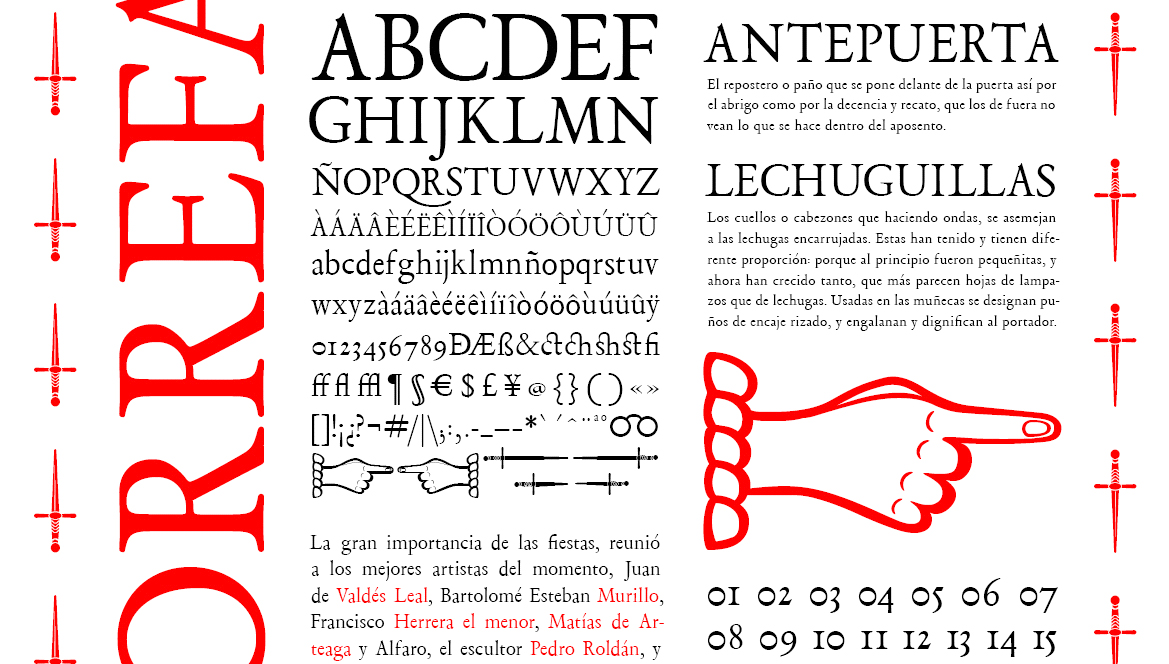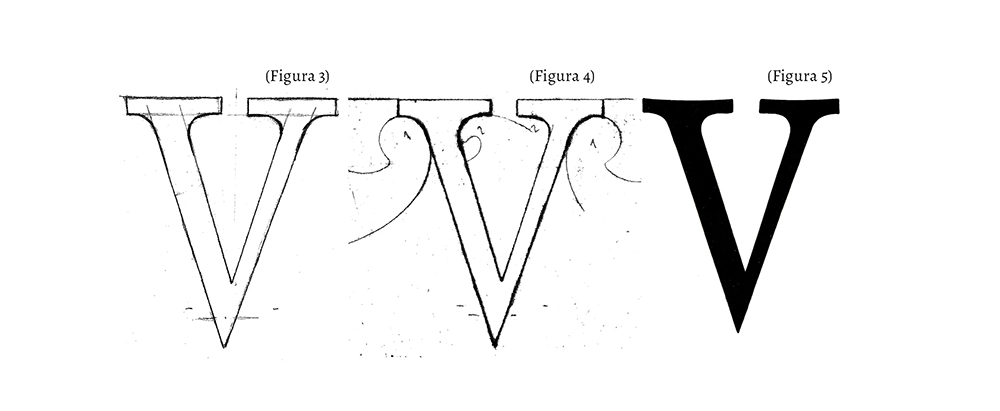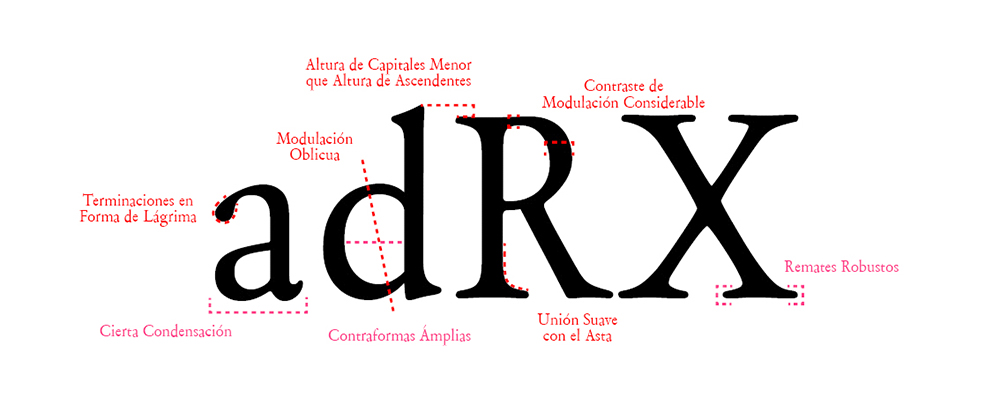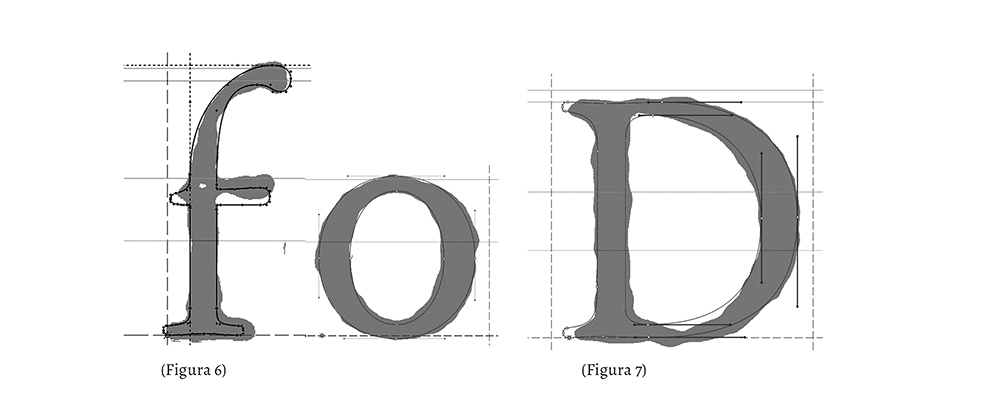
TorreFarfan es una remasterización digital tipográfica, que tiene su origen en la tipografía barroca del siglo XVII empleada en la impresión del libro realizado con motivo de la canonización de San Fernando, escrito por Fernando de la Torre Farfán del que procede el nombre de la fuente, e impreso en Sevilla en 1671 por la Viuda de Nicolás Rodríguez de Ábrego. La obra recoge la descripción de las fiestas que celebró la Santa Iglesia Catedral de Sevilla y está considerada una obra maestra de la tipografía hispalense y la mejor edición de libro impreso de la España del seiscientos.
La recuperación de esta fuente tipográfica es el resultado de una investigación histórica realizada para la elaboración del proyecto fin de Estudios Superiores de Diseño Gráfico de la Escuela de Arte de Sevilla realizado por Estefanía González Sánchez, diseñadora gráfica, y bajo la tutela de Javier Navarro Moragas, doctor en Bellas Artes por la Universidad de Sevilla y profesor en semiótica tipográfica en la Escuela de Arte de Sevilla. La realización de este proyecto pretende poner en conocimiento de aquellos a los que le pueda interesar la arquitectura tipográfica en el periodo dorado de la imprenta en Sevilla para así dar a conocer la manera de hacer en esta época y en esta región. Ello ha permitido traer al presente parte de un patrimonio andaluz no tan conocido, concretamente desde el prisma de la edición del libro impreso, que nos permite entender una parte importante de esta cultura.
Remasterizar la póliza tipográfica de tan importante edición bibliográfica dentro del marco cultural de la ciudad hispalense en el siglo XVII nos permite recuperar matices estéticos del pasado. Por otro lado nos ofrece conocimiento sobre la manera de trabajar el libro impreso y más concretamente la tipografía de la época de que se trata. Es una puerta abierta a la investigación histórica del gremio de impresores sevillanos del XVII que a la vez permite y pretende la búsqueda de una gráfica unificadora entre pasado y presente.
Este artículo ofrece un análisis del contexto histórico, un estudio morfológico de la fuente que incluye comparativas arquitectónicas, así como la descripción del procedimiento realizado con el fin de materializar la recuperación de esta póliza tipográfica.
Contexto Histórico
Durante un periodo de cinco días en el mes de mayo del año 1671, siendo papa Clemente X, y reinando en España Carlos II El Hechizado, Sevilla realizó un festival religioso en el que la ciudad fue decorada con elementos ornamentales y arquitectura efímera para celebrar la canonización del rey San Fernando el III de Castilla y León (1201-1252), proclamado héroe cristiano por la conquista de grandes extensiones territoriales de Al-Andalus en el año 1248 pertenecientes a la cultura almohade. El cabildo de la catedral hispalense encargó al sacerdote, cronista, poeta, escritor y traductor Fernando de la Torre Farfán la autoría del libro Fiestas de la Santa Iglesia Metropolitana, y Patriarcal de Sevilla, al Nuevo Culto del Señor Rey San Fernando, con el fin de describir dichas fiestas con todo lujo de detalle y dejar constancia escrita de estos hechos. La realización del libro pretendía ser una reafirmación de la Sevilla barroca y un intento de recuperar la grandeza perdida tras la peste que afectó a casi la mitad de la población, por lo que la Catedral financió y distribuyó dos mil copias a Universidades, Catedrales y a personalidades ilustres de todo el mundo.
La gran importancia de las fiestas reunió a los mejores artistas de la Sevilla de la época, Juan de Valdés Leal (1622-1690), Bartolomé Esteban Murillo (1617-1682), Francisco Herrera el Menor (1627-1685) Matías de Arteaga y Alfaro (1633-1703), el escultor Pedro Roldán (1624-1699), y al retablista Bernardo Simón de Pineda (1638 – 1702). Junto a esta nómina excepcional de artistas y como reza al pié del frontispicio del libro, encontramos que fue impreso en Sevilla en casa de la Viuda de Nicolás Rodríguez de Ábrego en la calle Génova. Una imprenta que debió despuntar con respecto a las otras treinta y dos que trabajaban por aquel entonces en la ciudad, equiparándose en calidad artística y maestría a la de aquellos artistas que colaboraron en la efeméride conmemorativa.
De Nicolás Rodríguez de Ábrego se conoce una parte interesante de su historia; imprime desde 1637 a 1671, momento en el que toma el relevo de la imprenta su viuda. El siglo xvii fue un tiempo de crisis en lo que al libro impreso se refiere –a diferencia de lo que sucedía en la primera mitad del siglo xvi– cuando Sevilla era el principal centro productor de libros de Castilla; en el xvii las ediciones impresas fueron muy pobres abundando las obras pequeñas impresas con tipos desgastados y papel de mala calidad. En este periodo surge un formato editorial denominado «Relaciones de Sucesos», antecedente a la prensa escrita que hoy conocemos. Fue parte de la producción de la imprenta de Nicolás; era de factura mediocre pero muy rentable ya que se trataba de tiradas cortas, fáciles de hacer y de bajo coste, gozando por ello de gran salida en el mercado diario.
Existen por otro lado documentos que recogen información relacionada con unos pleitos que Nicolás tuvo con la inquisición por sus trabajos como impresor; a finales de marzo de 1641 el oidor de la Audiencia sevillana Juan de Góngora, inspeccionó la imprenta de Nicolás Rodríguez y encontró miles de libros impresos sin haber «sacado liçencia […] ni mostrado privilegio para ello»,(2) por lo que fue condenado a prisión bajo fianza y se le confiscaron las obras y le fueron requisados los útiles de impresión, aunque Nicolás pudo pagar la fianza y no entró en la cárcel. Quizá todo ello podría haber llevado a Nicolás a realizar este tipo de tiradas de poca extensión, probablemente para incrementar sus beneficios y remontar su economía de una manera relativamente cómoda y ágil; además la ubicación estratégica de su imprenta le permitiría realizar un gran número de ventas debido al elevado flujo de transeúntes del que gozaba la calle Génova (hoy Avenida de la Constitución) por su gran actividad mercantil procedente de las Indias.
Durante este periodo muchas mujeres se hicieron cargo de las imprentas de sus maridos cuando estos fallecieron, pero pocas de ellas firmaban con sus propios nombres. Cierto es que lo peor que le podía acaecer a una mujer era enviudar ya que ella y su familia entraban en estado de desprotección económica y social. Estas circunstancias llevaban a muchas a casarse con otros hombres relacionados normalmente con el gremio con el fin de que estos pasaran a regentar sus imprentas. En determinadas situaciones las viudas podían entrar en el mercado laboral, otorgándoles la posibilidad de realizar una actividad empresarial que por ellas mismas jamás habrían podido realizar. En los gremios se les permitía continuar la producción de sus difuntos maridos siempre y cuando pagaran los cánones marcados, y
este es el caso de la Viuda de Nicolás Rodríguez de Ábrego. De ella se tienen pocos datos; existe constancia que imprimió de 1671 (año en el que podría haber fallecido Nicolás) a 1674, o al menos es el periodo en el que los libros que salían de sus prensas lo hacían bajo su nombre. Todos los impresos realizados por ella son religiosos, de mayor complejidad y de una calidad superior a la habitual en la imprenta de Nicolás, además su obra engloba varios libros de una gran exquisitez. Otra de sus joyas editoriales la encontramos en el libro de Regla y Constituciones de la hermandad de Nuestra Señora del Socorro de Sevilla, que data de 1673. En este libro para la ya desaparecida Hermandad del Socorro, la Viuda de Nicolás colaboró de nuevo con Fernando de la Torre Farfán quién realizó la labor literaria, y con Matías de Arteaga y Alfaro responsable de los grabados ilustrativos. La Viuda, cuyo nombre desconocemos hasta la fecha, se codeó con los mejores artistas de la época, aumentó la producción al heredar la imprenta de su marido, y del mismo modo modificó el enfoque editorial del negocio.
Otro hecho que demuestra su gran valía empresarial es que su labor no solo se centró en la realización de libros impresos, sino que la armonizó con la tarea de mecenazgo, siendo impresos a su costa por otros impresores, como Tomé de Dios Miranda, libros de gran valor cultural como, Síguense siete romances a lo divino..; siendo la autoría del séptimo de estos romances atribuida a Lope de Vega.
No cabe dudar de la maestría proveniente de los talleres de esta mujer impresora que tiene el honor de ser la editora de la obra más encumbrada del arte impresor español del seiscientos. Según la historiadora Amalia Sarriá Rueda, el libro de la Fiestas de Torre Farfán «Es una obra maestra de la tipografía hispalense a cuya perfección contribuyen la selección del papel, la cuidada tipografía y las soberbias ilustraciones grabadas».(2)
Estudios Morfológicos
Paralelamente a la investigación histórica, se realizó un estudio de la arquitectura de los glifos que componen la póliza tipográfica del libro Torre Farfán. En este estudio observamos características pertenecientes a una época de transición tipográfica, ya que observamos una morfología de romana clásica, pero con rasgos evolutivos que la acercan hacia lo que mucho más tarde serán las romanas modernas. Por un lado, observamos algunas características comunes con las tipografías Garaldas, propias del siglo anterior, y que tienen como punto de partida las tipografías creadas por Francesco Griffo para Aldo Manucio en 1495.
En el siglo XVI Antonie Augereau y Claude Garamond realizarán tipografías con características ya asentadas de las tipografías Garaldas. Algunos rasgos de las tipografías Garaldas son: modulación oblicua, contraste de modulación considerable, remates inferiores unidos de manera suave con el asta, terminales de la /a/c/f/r/ con acabado en forma de lágrima, altura de las capitales menor que la de los astiles ascendentes..
La póliza utilizada por la Viuda de Nicolás Rodríguez tiene las características mencionadas, y por ello se engloba dentro de las tipografías Garaldas, pero también presenta rasgos modernizados que la situan en el marco espacio-temporal de las tipografías Barrocas o de transición, tan características desde mediados del siglo XVII hasta el siglo XVIII. Las tipografías de transición son un paso intermedio entre las romanas clásicas y las romanas modernas y tienen su punto de partida en la arquitectura de la Romain du Roi. Tienen muchas similitudes con las características de los tipos de Grandjean del siglo XVII. Algunos de estos rasgos podemos observarlos en nuestra tipografía, pero lo que sí es cierto es que en nuestro caso nos encontramos en un periodo temporal anterior a la creación de la Romain du Roi, por lo que se observa claramente que son tendencias que ya se venían dando en periodos anteriores y que estas características morfológicas serán recogidas y homologadas posteriormente por Grandjean en su Romain. Algunas características de las tipografías barrocas son: cierta condensación, contraformas amplias, remates robustos; estas características también podemos encontrarlas en nuestra tipografía.
Las tipografías de transición o barrocas se desarrollaron principalmente en Holanda, Inglaterra y Francia, pero el país con mayor peso en el ámbito de la tipografía fue Holanda, y en general los Países Bajos. Estas morfologías coinciden con los rasgos arquitectónicos própios de la época en la que se imprimió el libro, por lo que podemos decir que la tipografía usada para crear el libro de las fiestas de San Fernando era una tipografía vanguardista en su época, y no recuperada de tiempo atrás como era costumbre en este periodo.
En nuestra búsqueda por encontrar la identidad de la tipografía que nos ocupa nos encontramos con las pólizas empleadas en la prensa de la Universidad de Oxford, unas pólizas que tienen un adn similar a la empleada por la Viuda. Justo en ese mismo espacio temporal, concretamente un año más tarde de la impresión del libro de las fiestas de San Fernando, en el Reino Unido, John Fell –obispo y Vice-Canciller de la Universidad de Oxford–, creará la prensa de dicha universidad, y las tipografías empleadas pasarán a conocerse en aquella zona como «Tipos Fell». Dotó a su imprenta de las mejores tipografías existentes en el momento y para ello mandó comprar las pólizas más modernas y mejor realizadas de toda Europa. Para Fell el mejor lugar en el que podía abastecerse de las pólizas de mejor calidad era Holanda, ya que consideraba que la escuela tipográfica más exquisita residía en la estela de los punzonistas Garamond, Granjon y Van Dijk. Posteriormente, en la imprenta de Fell, estas pólizas fueron utilizadas para realizar impresiones de relevancia, como las ediciones de lujo, característica que también compartirá con la mujer impresora del libro de Torre Farfán. De las pólizas que adquirió Fell, destacamos unas romanas y unas itálicas inglesas, que son similares a las utilizadas por la Viuda. Las romanas y las versales fueron cortadas por Cristoffel Van Dijck y las itálicas por Robert Granjon y fueron adquiridas por Fell en 1672.
Entendemos que en la imprenta de la Viuda de Nicolás se conocían las tendencias tipográficas que se estaban dando en el momento, también sabemos que el Cabildo de la ciudad de Sevilla repartió dos mil copias del libro a los dignatarios más importantes de todo el mundo ¿Podría la Viuda de Nicolás, haberse convertido en modelo editorial, y de ese modo influir en la imprenta de la Universidad de Oxford, con la que compartía tantas características?
Cierto es que por el momento no hemos encontrado la identidad de la Viuda y no conocemos su historia, pero podemos estar seguros que se dedicaba a este oficio mucho antes de la realización del libro de Torre Farfán y que en su taller existía un gran nivel impresor, comparable con el proveniente de las principales capitales europeas en cuanto a arte tipográfico se refiere, y por supuesto quedó de manifiesto en esta obra.
Remasterización digital
En primer lugar, y con el fin de definir una tabla de caracteres adecuada, es preciso determinar las cualidades que va a cumplir nuestra tipografía, que vendrán sujetas por el uso que queremos que esta tenga. En nuestro caso, la fuente se realizó para texto corrido en prosa literaria, en castellano, y para uso actual. Esto nos llevó a realizar glifos como la /w/ o la /k/, partiendo de la morfología de otros de nuestro alfabeto que compartían similitudes arquitectónicas, ya que estas letras no se emplearon en el libro impreso. Además para ralizarlos acudimos a fuentes de estética paralela como la «Tipos Fell»descrita anteriormente con el fin de salvaguardar la analogía. Para nuestra tipografía se realizaron los glifos en minúscula y mayúscula, y vocales acentuadas; también se realizaron numerales elzevirianos, signos de puntuación, ligaduras y símbolos relacionados con el momento histórico al que pertenece.
Una vez definida la tabla de caracteres pasamos a la fase de digitalización de nuestra póliza realizando un estudio visual previo de cada uno de los glifos, agrupandolos por analogías formales según la metodología de Karen Cheng en su libro Diseñar tipografía. Esto nos facilitó la tarea posterior de digitalización del resto de la póliza. Los glifos por los que empezamos son /v/o/n/ de los que saldrán las siguientes relaciones:
- Del glifo /n/ derivan: /u/ñ/m/h/i/j/l/r/
- Del glifo /o/ derivan: /c/e/d/b/q/p/
- Del glifo /v/ derivan: /w/x/y/z/k/
- Los glifos /f/t/ guardan cierta similitud
- Los glifos /a/s/ pueden relacionarse con el /o/
Para las mayúsculas, el primer glifo que realizamos fue /H/, ya que su espesor se relaciona con /n/ que determinará el espesor del resto de mayúsculas:
- Del glifo /H/ derivan: /E/F/I/L/T/
- Del glifo /O/ derivan: /C/Q/G/D/
- Del glifo /B/ derivan: /P/R/
- Del glifo /U/ derivan: /J/
- Del glifo /N/ derivan: /Ñ/M/Z/
- Del glifo /A/ derivan: /V/W/X/K/Y/
- Del glifo /S/ no deriva ningún glifo
Claras las relaciones entre arquitecturas pasamos a la metodología de recuperación tipográfica de Javier Navarro Moragas. Para ello agrupamos un número considerable de glifos iguales del libro impreso, para comparar las manchas y entender sus formas (Figura 1).
Esta comparativa permite realizar un estudio a lápiz, dibujando varias veces la forma de la letra y sus detalles, con el fin de dejar definida la arquitectura (Figura 2), para posteriormente realizar un dibujo a mano alzada definitivo (Figura 3). Este dibujo a mano alzada lo reproducimos de nuevo haciendo uso de unas reglas de formas, consiguiendo unas líneas depuradas para posteriormente entintarlas (Figura 4 y 5), y llevar nuestro glifo como plantilla al programa de creación de fuentes digitales elegido (Figura 6).
Ya digitalizadas las minúsculas, ajustamos el track con el fin de que la mancha tipográfica presente una textura uniforme. Dispusimos unos seis o siete glifos /n/ uno tras otro y, teniendo como referencia el track del libro Fiestas de Torre Farfán, ajustamos las prosas de manera que visualmente quedaran tanto la izquierda como la derecha equivalentes. Al hacerlo con este método conseguimos determinar las prosas para la mayor parte de los glifos del alfabeto, ya que este procedimiento nos otorga la medida para glifos que tienen rectas en sus extremos y glifos que tienen pequeños entrantes o curvas. Posteriormente hicimos lo propio con el glifo /o/, que tiene curvas en todo su contorno, y sirve de pauta para los glifos con el mismo comportamiento. Dispusimos una serie de /o/ y buscamos un track cercano, al mismo que le dimos a la /n/ (Figura8). Una vez realizado procedimos a ajustar los tracks de los glifos que consideramos semejantes en comportamiento y les otorgamos las medidas correspondientes, relacionadas con los glifos /n/ y /o/. Para los glifos con arquitecturas distintas y que presentan comportamientos diferentes en su relación con otros glifos como por ejemplo /f/, se dispusieron una serie de glifos /f/ junto con /n/ y /o/, y se ajustaron visualmente hasta que se observaron tracks similares. Este procedimiento lo repetimos de la misma manera para las mayúsculas.
El último ajuste lo realizamos entre pares de letras que tienen un comportamiento particular como el par de letras /f/ /n/ con la herramienta kerning de FontLab (Figura 9), y ajustamos ópticamente la distancia con respecto a pares de letras de comportamientos uniformes.
Una vez terminada la tipografía en su versión regular, creamos un pack (Figura 10) para presentar la póliza remasterizada que incluye un espécimen que muestra su comportamiento para diferentes tratamientos de texto. Muestra un carácter editorial que recuerda al estilo bibliográfico utilizado en el barroco sevillano y más concretamente el empleado en este libro de Torre Farfán; esto nos permite hacer un guiño a la estética de estilo setecentista y unirla a la estética contemporanea a través del diseño editorial y del uso de símbolos y glifos como imágenes, haciendo uso de la semiótica tipográfica con el fin de unir dos universos dentro de un marco cultural común pero distantes en el tiempo.
Conclusiones
La realización de este proyecto ha generado líneas abiertas de investigación como por ejemplo la situación de la mujer impresora en ese periodo, la tipografía de la edad de oro en la imprenta sevillana y española, y el gremio tipográfico en la Sevilla del siglo XVII.
Otra vía de investigación es la identidad de la Viuda de Nicolás Rodríguez. Por nuestra parte hubiésemos querido homenajear a esta mujer impresora, concediendo su nombre a nuestra tipografía pero no ha sido posible. Durante el periodo de investigación realizado hemos llegado a barajar varias hipótesis sobre la identidad de esta mujer, y es nuestra preferencia por el momento la que otorga a la Viuda de Nicolás el nombre de Doña María de Quiñones (coincidiendo con el nombre de la famosa impresora madrileña de cuyas prensas salió la primera edición del Quijote). Estas investigaciones, realizadas en varios archivos históricos de la capital hispalense, siguen su curso a día de hoy; y esperamos poder encontrar por fin la identidad exacta de la Viuda, así como mayor información sobre su historia.
Notas
(1) Calvo Poyato, José. Un proceso a impresores y libreros en la Sevilla del Barroco. Sevilla, Archivo hispalense, 1987.
(2) Sarriá Rueda, Amalia. La imprenta en el siglo XVII. Madrid, Fundación Germán Sánchez Ruipérez, 1994
Bibliografía
Calvo Poyato, José. Un proceso a impresores y libreros en la Sevilla del Barroco. Sevilla, Archivo hispalense, 1987.
Caracuel Moyano, Rocío y Guzmán Dominguez, Aurora. Un tesoro en la Universidad de Sevilla: incunables y obras de los siglos xvi y xvii. Sevilla, Editorial Universidad de Sevilla, 1993.
Dadson, Trevor. Libros, lectores y lecturas. Estudio sobre bibliotecas particulares del Siglo de Oro. Madrid, Arco libros, 1998.
Dominguez Guzman, Aurora. «Relaciones de autos de fe impresas en el siglo xvii» url:https://dialnet.unirioja.es/servlet/articulo?codigo=1214913
Domínguez Guzmán, Aurora. La imprenta en Sevilla en el siglo xvii: 1601-650. Sevilla, Universidad de Sevilla, 1992.
Domínguez Guzmán, Aurora. Nueva revisión de la tipografía hispalense. Sevilla, Editorial Universidad de Sevilla, 2005.
Escudero y Pedrosso, Francisco. Tipografía Hispalense: anales bibliográficos de la ciudad de Sevilla desde el establecimiento de la imprenta hasta finales del siglo XVIII. Madrid, sucesores de Rivadeneyra, 1894.
García de Enterria, María Cruz, Ciudades e impresores en la España del siglo xvii especializados en la edición de pliegos de cordel, libro homenaje a Antonio Perez Gomez. Cieza, 1978.
Gestoso y Pérez, José. Ensayo de un diccionario de los artífices que florecieron en sevilla desde el siglo xiii al xviii inclusive. Sevilla, Sauceda,1900.
Hazañas y la Rua, Joaquín. La imprenta en sevilla: ensayo de una historia de la tipografía sevillana y noticias de algunos de sus impresores … Sevilla,1892.